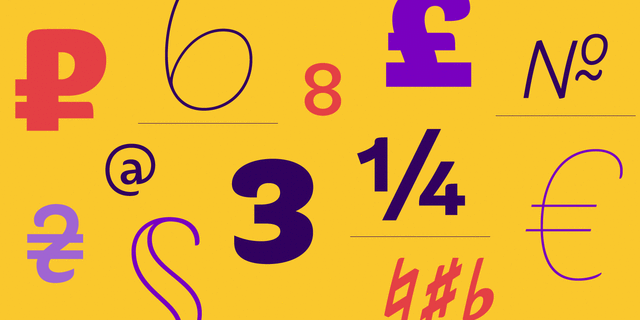
Практичный гротеск не обязан быть строгим, вычерченным или привычным. Он может преуспеть в своей собственной роли и сохранить уникальное настроение. Iskra (Искра или вспышка) – новый шрифт без засечек, разработанный Томом Грейсом. Он был задуман как вызов разделению между утилитарными и декоративными шрифтами. Его привлекательные формы отсылают к лихому кистевому леттерингу и содержат смелые, элегантные изгибы, экономные пропорции и небольшую вертикальную асимметрии. Теплота этого шрифта происходит из-за акцента на оригинальности конструкции и деталях отдельных букв, тогда как его солидность проявляется в его сбалансированном ритме в больших объемах текста.
Каждое начертание шрифта поддерживает более 60 языков и старательно адаптировано вручную для использования как в печати так и на экране. Iskra содержит 14 начертаний и отлично подходит для презентаций, журналов, брендинга и рекламы.
Шрифт разработан Томом Грейсом в 2011 году.
Ассоциации c начертанием Iskra CYR Ultra ThinКачества и характер:
деликатный, аккуратный, лаконичный, качественный, холодный, худой, легкий, тонкий, чистый, невесомый, прозрачный, воздушный